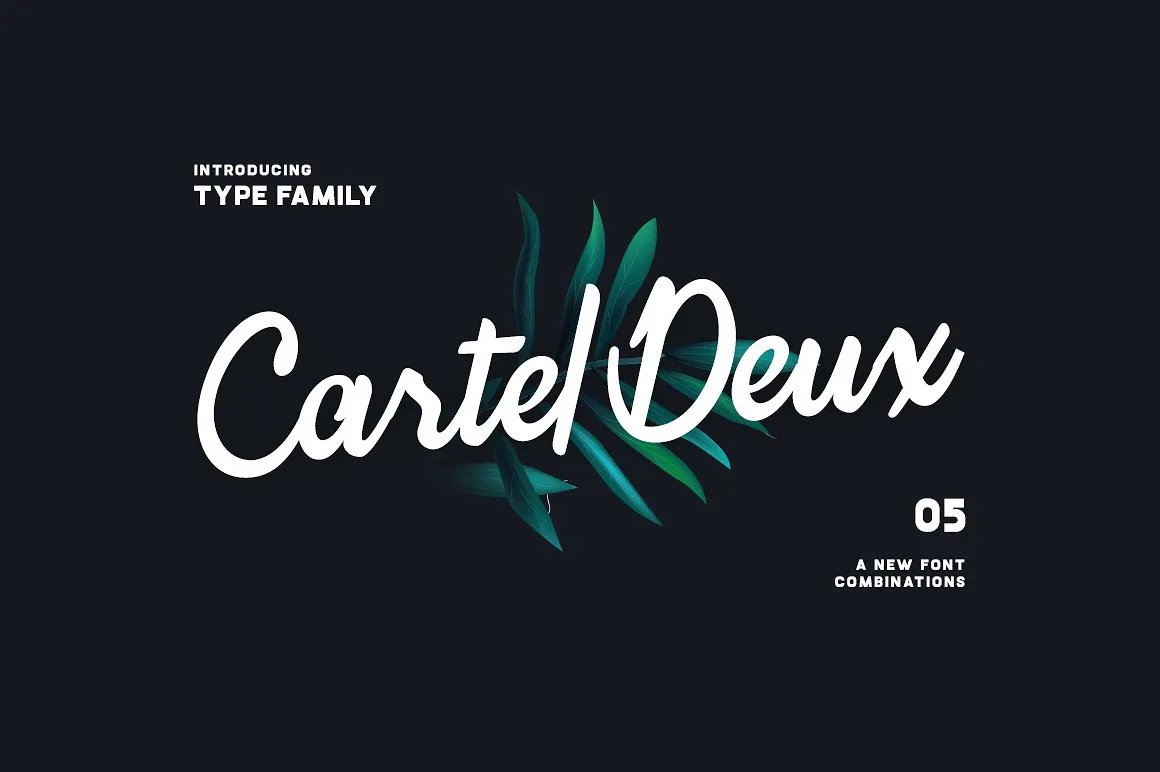
Cartel Deux Script Font Family – Download Grátis
Introduzimos a Font Family Cartel Deux Script! Desenhada e compartilhada pelo designer CartelDeux™, a Cartel Deux é uma nova tipografia que reúne elementos de tipo script e bold, oferecendo diferentes estilos entre Smooth & Sharp Script. Este set completo inclui cinco estilos únicos. A cartel Deux Script foi criada por Hamilton para ser uma fonte versátil, adequada para uso em diversas aplicações gráficas. Suas linhas agradáveis e elegantes permitem que o texto fique harmonioso tanto em designs mais formais quanto em um ambiente mais casual. A Cartel Deux oferece estilos que variam desde texturas fluidas e finos até formas rígidas e marcantes, permitindo aos designers criar layouts dinâmicos e atraentes. Este é um excelente conjunto de fontes para aqueles que buscam uma opção diferente do tradicional tipo script – cada estilo traz seu próprio charme à sua arte. Com os cinco estilos disponíveis na Cartel Deux Script, a variedade criativa ficará ao alcance dos designers, permitindo personalizar o layout e destacar seus textos de maneira única.